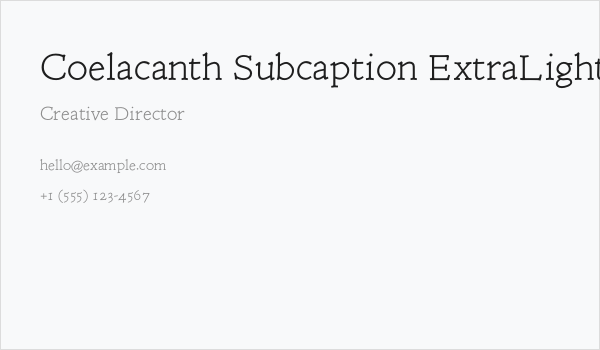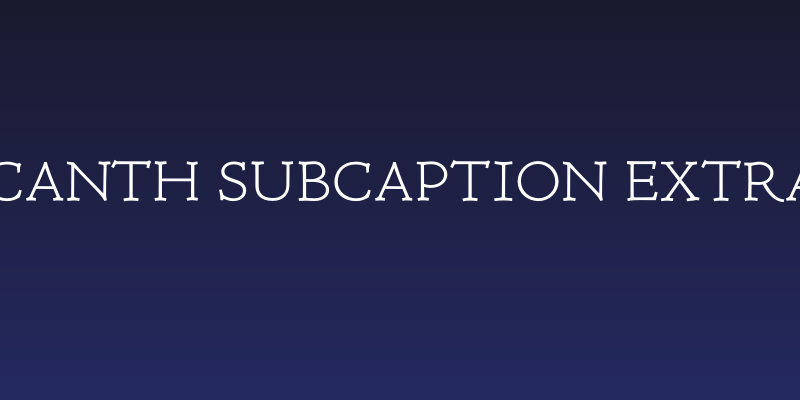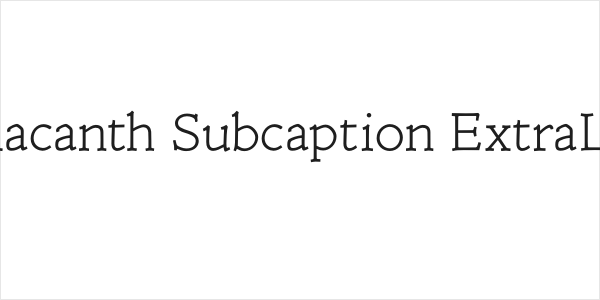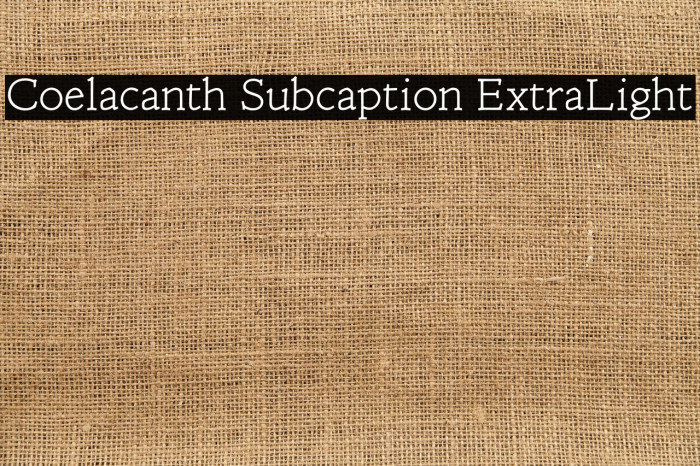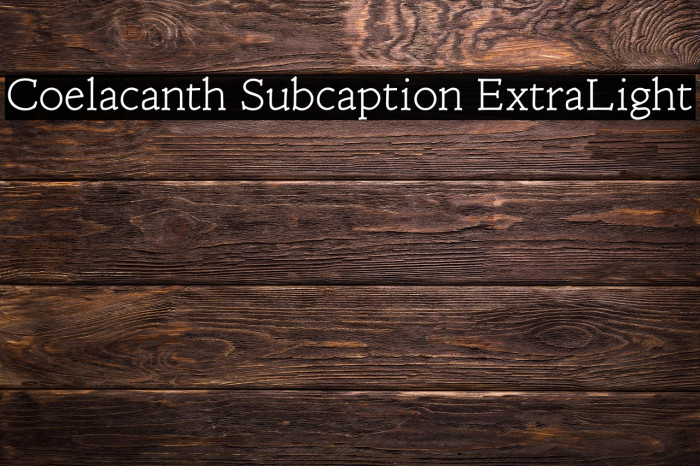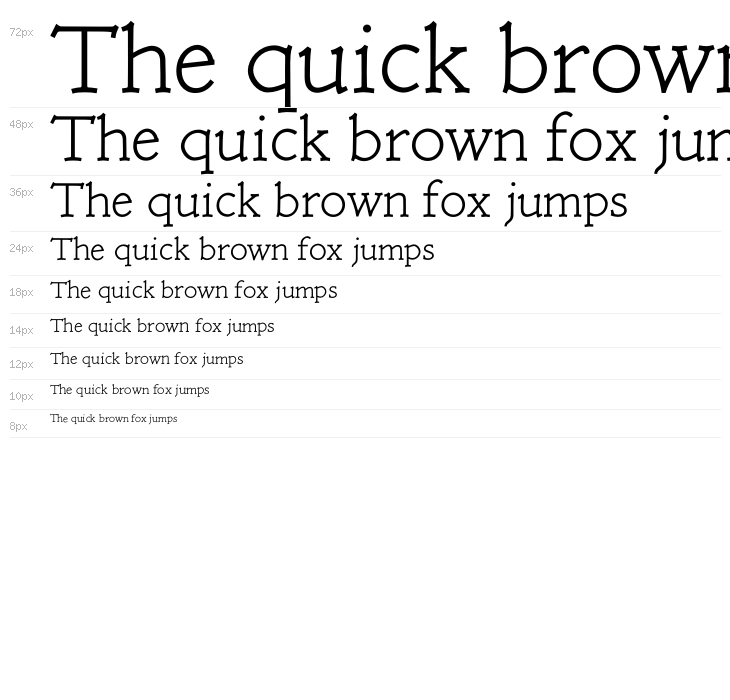
Coelacanth Subcaption ExtraLight Font
| النمط العام | Classic |
| حالة الاستخدام | Headlines, Body text, Logos |
| مشاريع مقترحة | Ideal for projects requiring a touch of elegance, such as wedding invitations, luxury branding, editorial layouts, and sophisticated web design. |